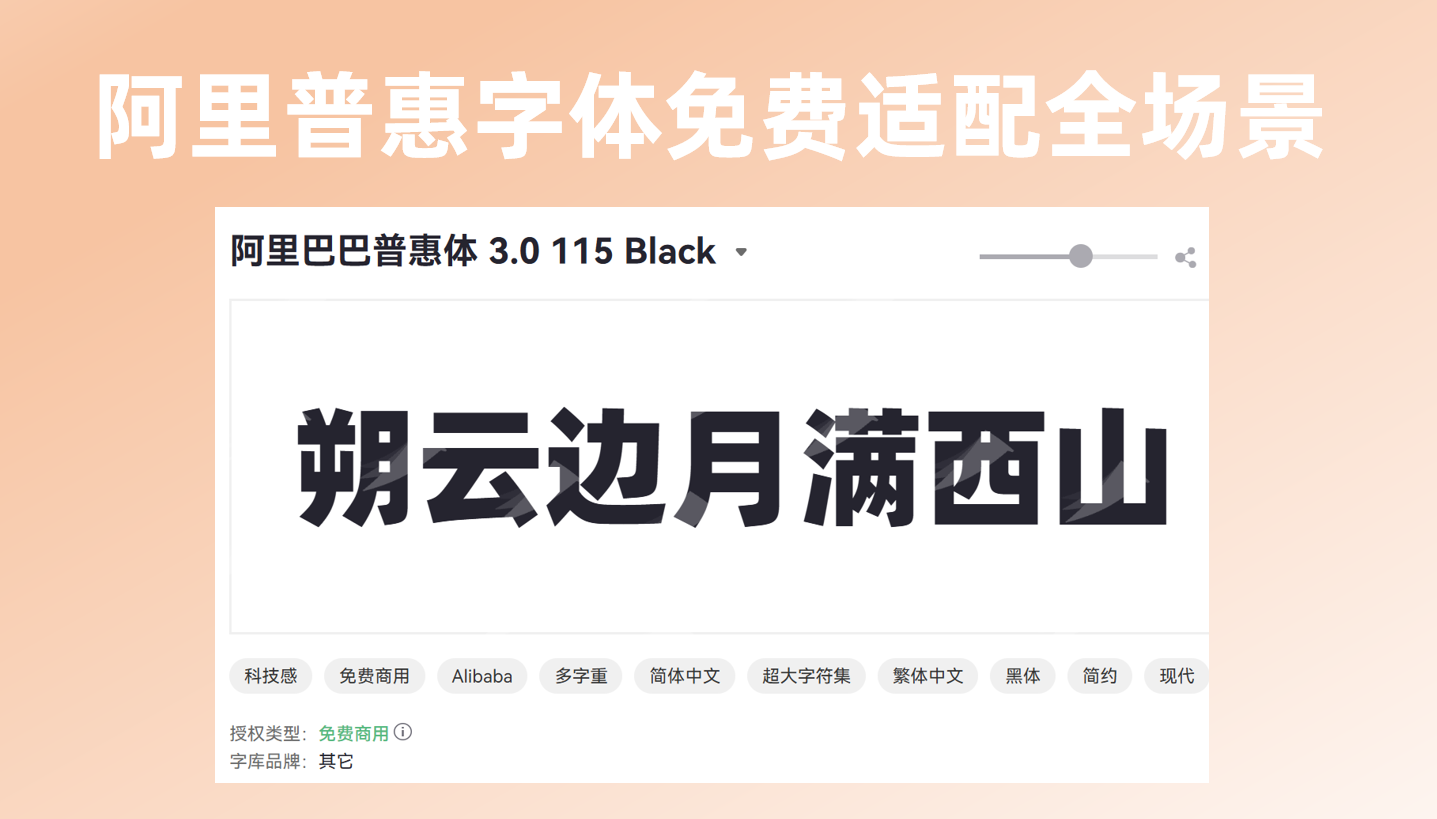
找字体别愁!阿里普惠字体免费适配全场景
阿里普惠字体的出现,彻底打破了这一僵局。作为阿里巴巴推出的全球永久免费商用字体,它涵盖178个语种,收录超19万个全形汉字,符合GB18030-2022新国标,从政务服务到商业推广都能安心使用。其9种字重选择可满足标题、正文等不同层级排版需求,无论是屏幕显示还是印刷输出都清晰易读。想轻松拿到这款“宝藏字体”?本文推荐的这4个阿里巴巴普惠体下载平台亲测好用,全场景需求都能hold住。
100font是个主打“免费商用字体聚合”的平台,整理阿里普惠字体特别细致,很适合追求轻量化的朋友。不像官网要下完整包,它把字体按字重、语种拆分开了,你要是只需要Regular常规字重,或者只用到中文部分,单独下载就行,能省不少存储空间。对于不太懂字体搭配的新手,它还贴心标了适配场景——比如Regular字重读起来舒服,适合做正文;Heavy粗体视觉冲击力强,做海报标题刚好。